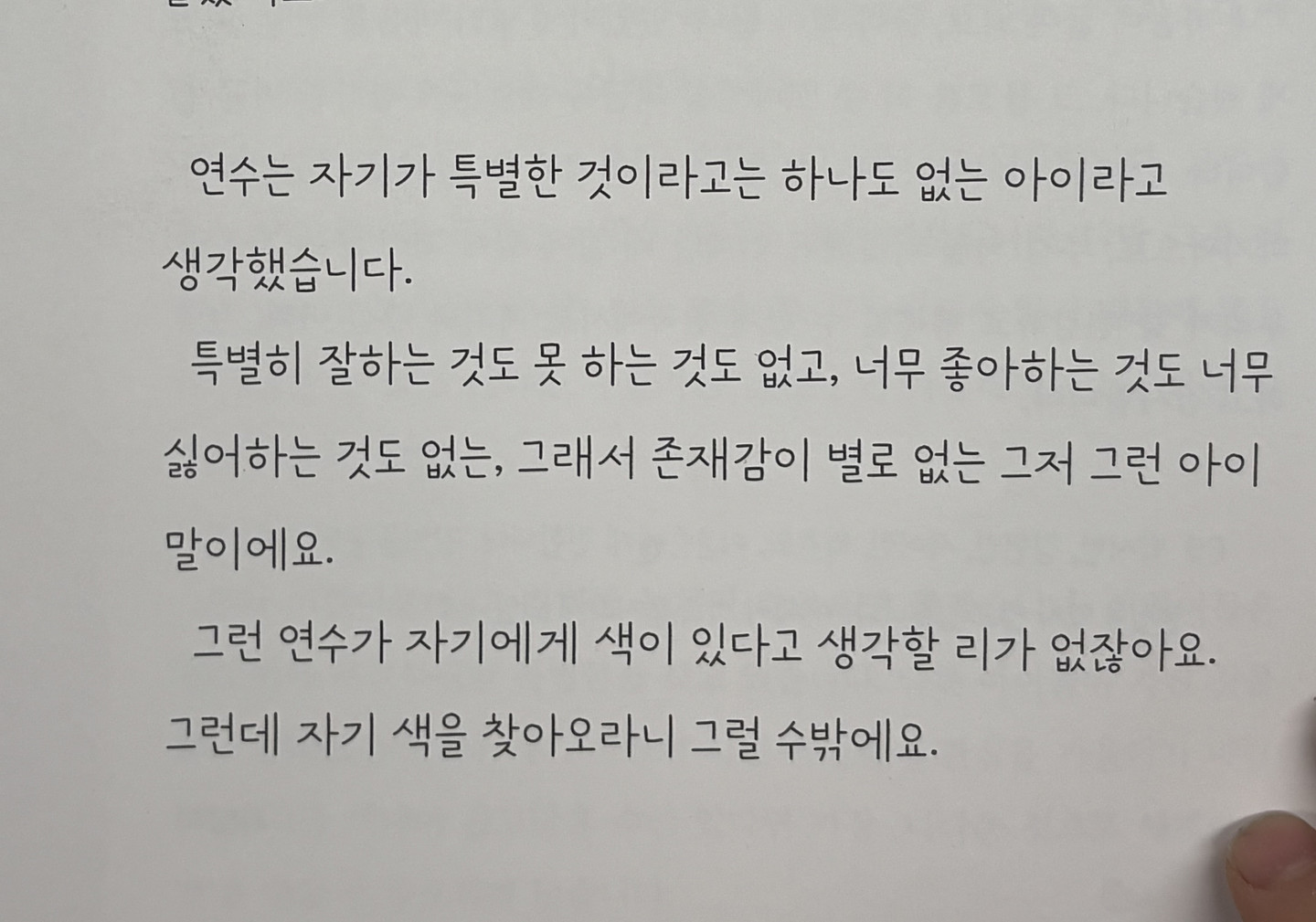
교회 피피티 폰트 복구중인데 찾아주실수있나요? ㅠ.. "ㅇ" 이 중간에 끊겨있고 몇몇글자들은 경계선없이 붙어있는게 포인트예요! 배민 도현체가 뜨긴하는데 그걸 사용하면 "ㅇ" 이 안끊겨있더라구요..
눈누에서 지정해 놓은 한자 기본체인거 같아요. 실제로 저 폰트들은 한자 지원을 하지 않더라구요. 그런데 저 눈누에서 지정해 놓은 한자 폰트가 너무 예뻐서요. 어떤 폰트인지 알 수 있을까요?
학교 시험지나 관공서에 자주 등장하는 폰트인거 같은데 혹시 이거 무슨 폰트일까요? ㅠㅠ 자주 본 것 같아서 눈에 익은데 폰트를 못 찾겠어요..